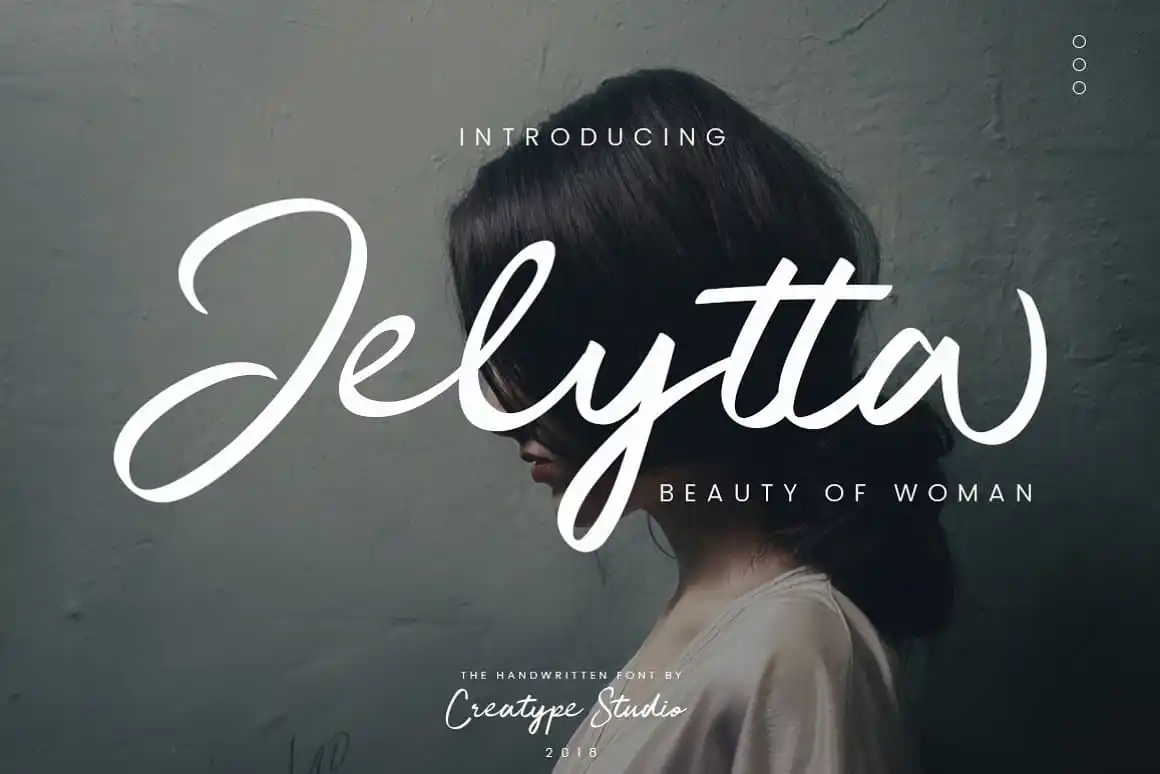
Introduzimos Jelytta, uma nova e encantadora fonte escrita a mão. Desenvolvida pela Creatype Studio Co., Jelytta captura a beleza feminina com suas nuances suaves, tornando-a sofisticada, elegante e impecável para diversos projetos digitais. Jelytta é perfeita para aplicações que exigem um toque único da mão humana, como fotos, postagens em mídias sociais, embalagens de produtos, selos, convites, campanhas publicitárias e até mesmo design wedding. Seu traço ondulado garantirá que seu trabalho brilhe ainda mais, tornando-o perfeito para qualquer uso que precise de um toque autêntico da escrita à mão. Jelytta oferece uma textura suave e elegante que se adapta facilmente a vários estilos de design, tornando-a uma escolha ideal tanto para aqueles que querem adicionar um pouco de personalidade à sua identidade visual quanto para aquelas pessoas que buscam um toque delicado em projetos digitais.